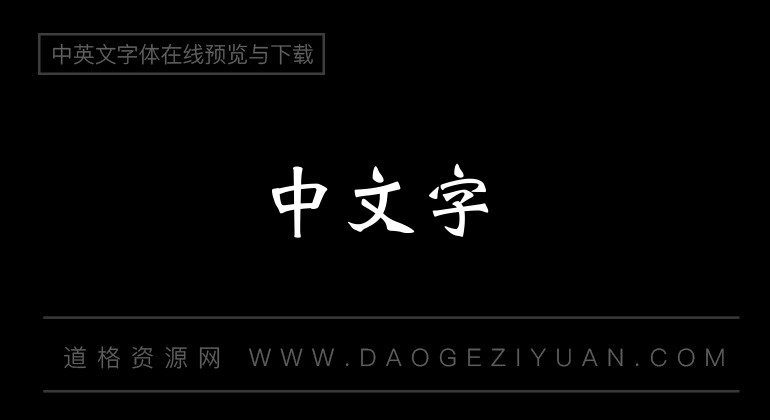
华康魏碑体外字集
华康魏碑体外字集是一款由华康设计的中国古典文字外字体,它采用了古代魏碑体的设计理念,以一种更加传统的方式来表现中国古典文字。字体具有极高的视觉冲击力,拥有较宽的视觉范围,可以将文字更加清晰、精致、美观地表现出来。字体也拥有较强的可读性,可以使文字更加清晰、易读,从而起到传播文字的作用。
华康魏碑体外字集是一款非常不错的手写艺术字体,具有很好的视觉感,适合于文化类的宣传设计、商业类品牌的广告和产品包装设计以及个性化文字排版等较多场景。